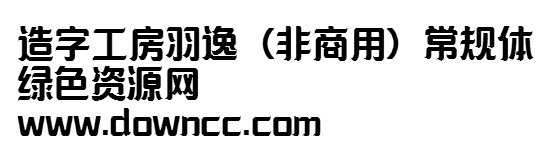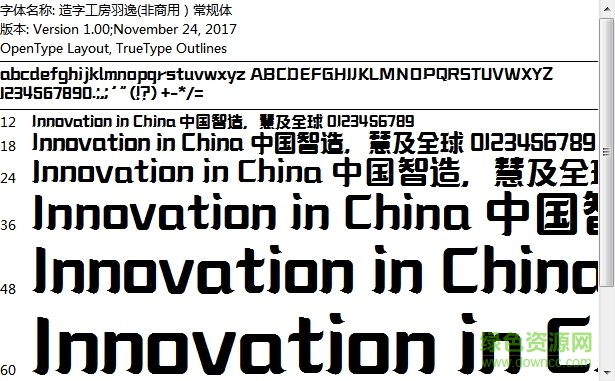
造字工房羽逸是一款非商用的藝術(shù)設(shè)計(jì)字體,自帶加粗加黑設(shè)計(jì),筆畫(huà)有著圓潤(rùn)的末梢,看起來(lái)比較生動(dòng)有趣,給大家?guī)?lái)了十分出色的藝術(shù)體驗(yàn),來(lái)綠色資源網(wǎng)免費(fèi)下載吧!
造字工房羽逸(非商用)常規(guī)體是一款非常漂亮的藝術(shù)字體,具有強(qiáng)烈的視覺(jué)沖擊力,廣泛用于各種書(shū)刊、畫(huà)冊(cè)的設(shè)計(jì)印刷、個(gè)性促進(jìn)品牌標(biāo)志設(shè)計(jì)、字體設(shè)計(jì)等環(huán)境,是報(bào)紙和雜志和書(shū)籍中常用字體。
造字工房羽逸字體是造字工房官方2017年推出的特色美術(shù)字體,在每個(gè)漢字的筆畫(huà)末梢,添加了圓潤(rùn)的處理,如同羽毛輕輕勾勒,給你的設(shè)計(jì)增添獨(dú)特魅力。